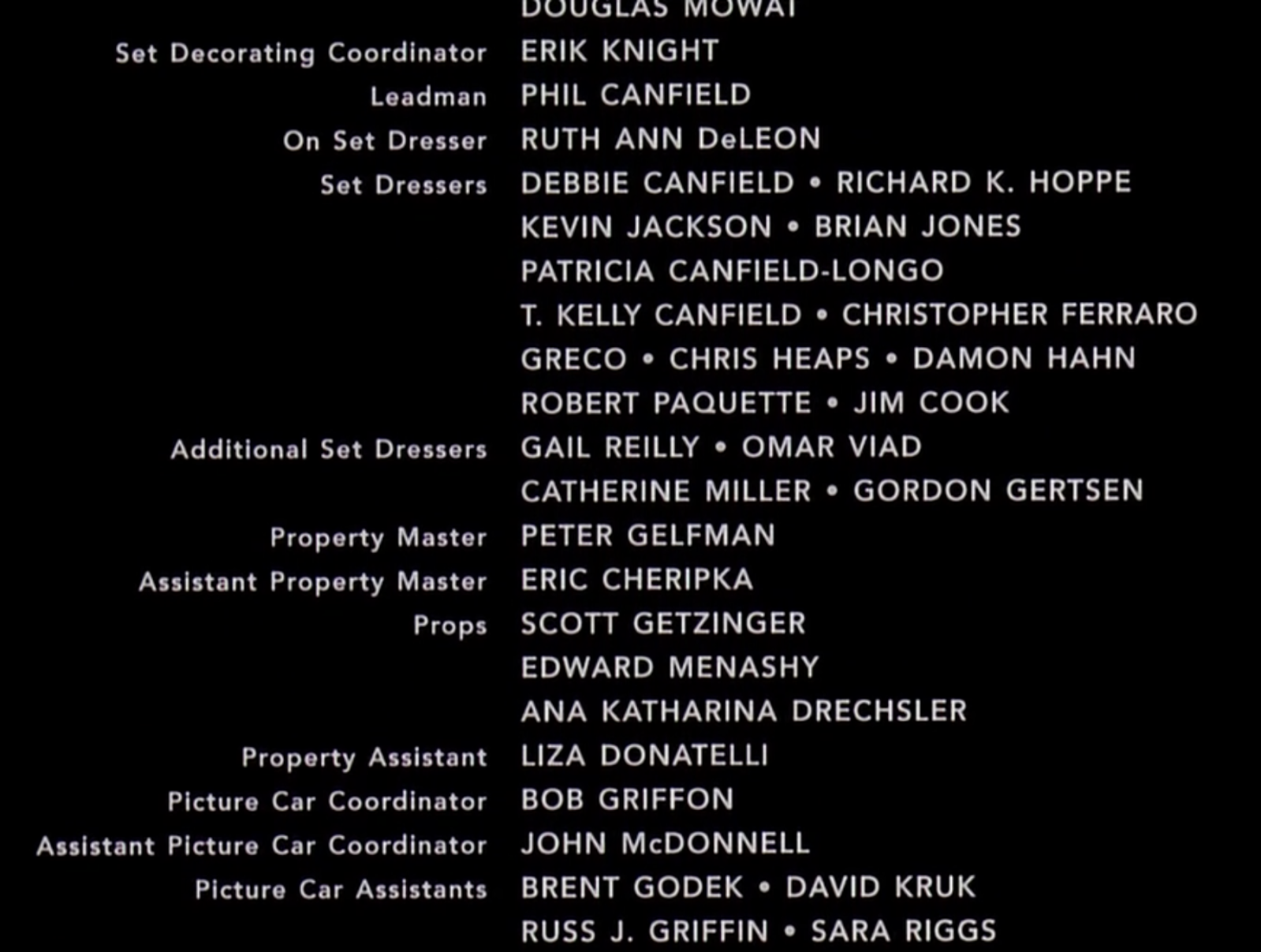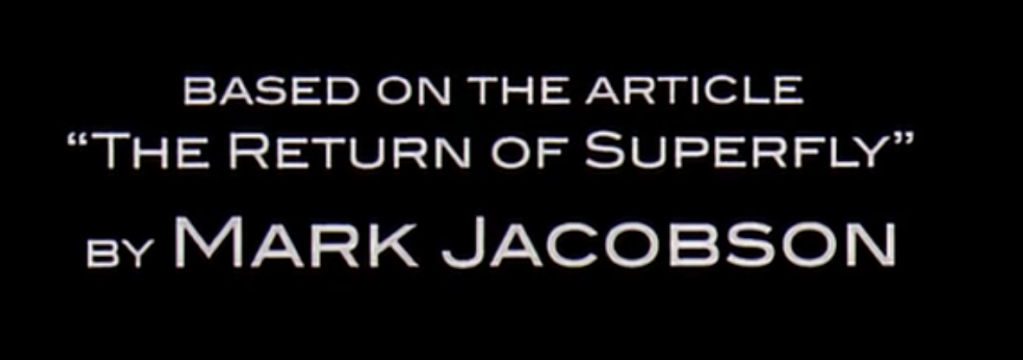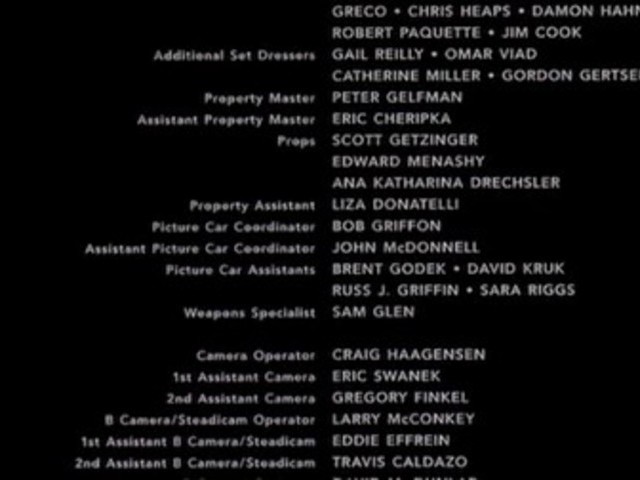
Kann mir jemand sagen, welche Schrift das ist? Bzw., noch wichtiger, welche gratis Schrift da am ehesten drankommt?
Arial …
Bei so einer Vorlage versagt meine Glaskugel.
Wem's weiterhilft: Es ist der Abspann zu "American Gangster" (2007). Ich habe leider auf die Schnelle keine aufschlussreicheren Bilder oder Videoausschnitte gefunden, jedenfalls keine legalen. Und die Schrift ist zu uncharakteristisch für meine begrenzten Schrifterkennungsfähigkeiten. Aber der Ehrgeiz, mal schneller zu sein als bertel, war immerhin geweckt ... ;-)
Aber diese ITC Blair sind ja nur Großbuchstaben im Set, oder?
Und gibt's die auch als Gratisversion wo? Und vielleicht nicht ganz so stark gestaucht? (Weil ich glaub, die im Gruppenabspann ist höher und eine andere als das mit MarcJacobson..., nicht?
Das Problem: selbst im 720p-Nachspann ist die Sxchrift einfach zu unscharf und zu klein, alsdass man hier den Font bestimmen könnte. Die x-Höhe beträgt gerade einmal 18 Pixel, die Linien sind etwa drei Pixel breit, aber in gleicher Größe unscharf. Hier ist es eigentlich unmöglich einen Font zu bestimmen, außer das es offensichtlich eine serifenlose Linearantiqua ist.
Wenn dir auch ähnliche Fonts reichen, dann schau mal nach Avenir, Soleil oder Gotham. Die Montserrat wäre dann die Freefont-Alternative dazu.